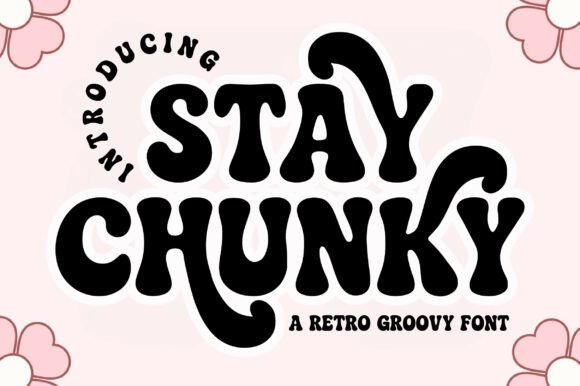
Stay Chunky
適切なデザイン要素を見つけるのは難しい場合がありますが、Stay Chunkyは作品を即座に引き立てる優れたコレクションを提供します。
POD(オンデマンド印刷)製品、結婚式の招待状、またはソーシャルメディアのグラフィックを作成している場合でも、Stay Chunkyは理想的です。